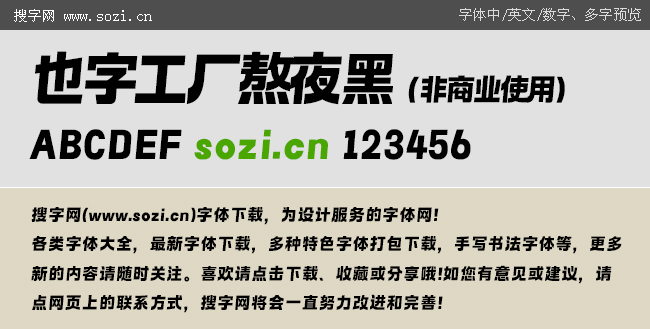
也字工厂熬夜黑
搜字网给大家提供一款也字工厂熬夜黑(非商业使用)中文字体下载,也字工厂熬夜黑整体特点是略微往右倾斜5°,笔画采用直线状的横竖笔画,给人以稳定和刚毅的感觉。折笔的部分笔画采用圆弧设计,横画稍细的特点,为字体增加了动感,让字形更加生动有趣。而起笔和收笔切面的整齐划一,使字体线条更加整洁和有序。 适合应用于海报设计、包装设计等应用(此字体为个人非商用版,商用可以联系:官方网址:https://yefont.com/home,联系方式:13798980448)。